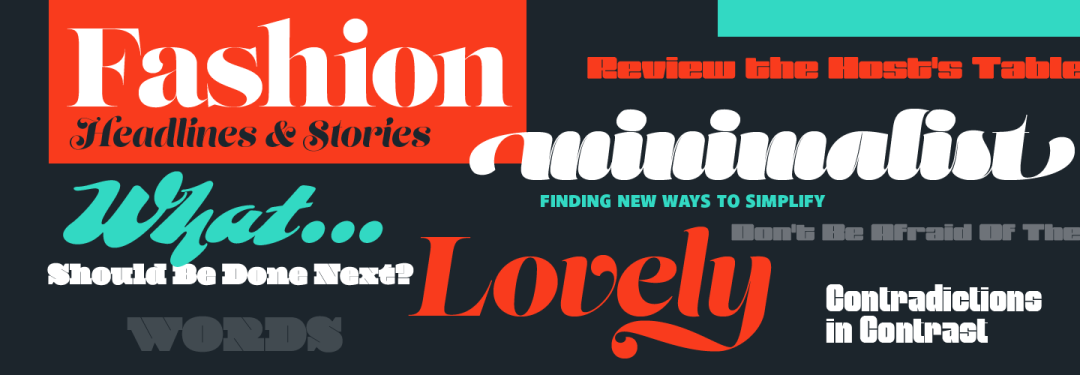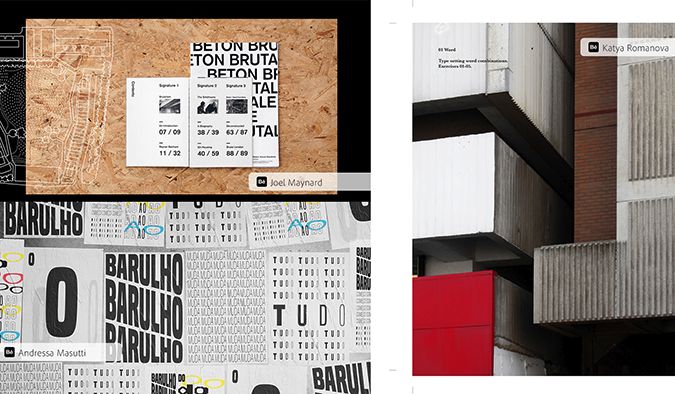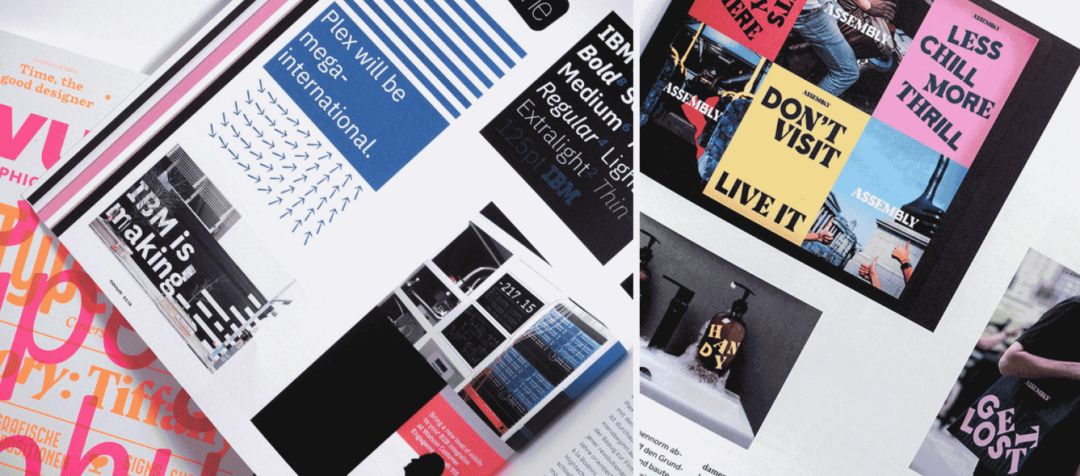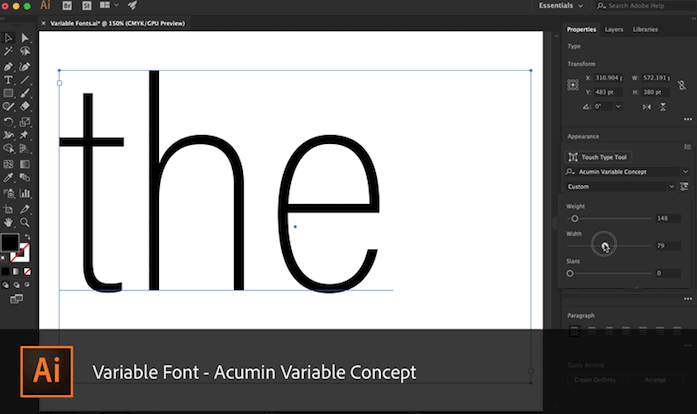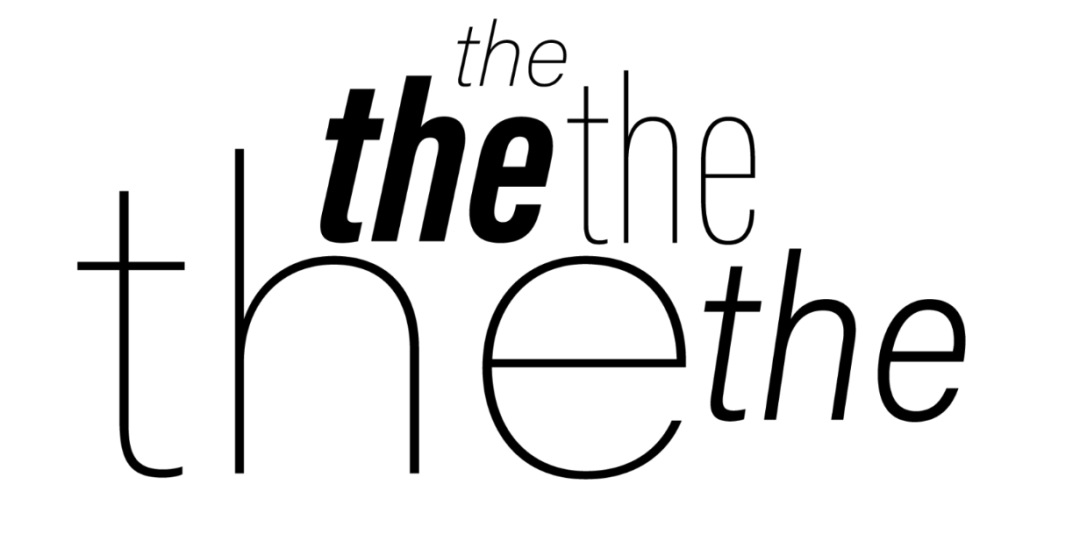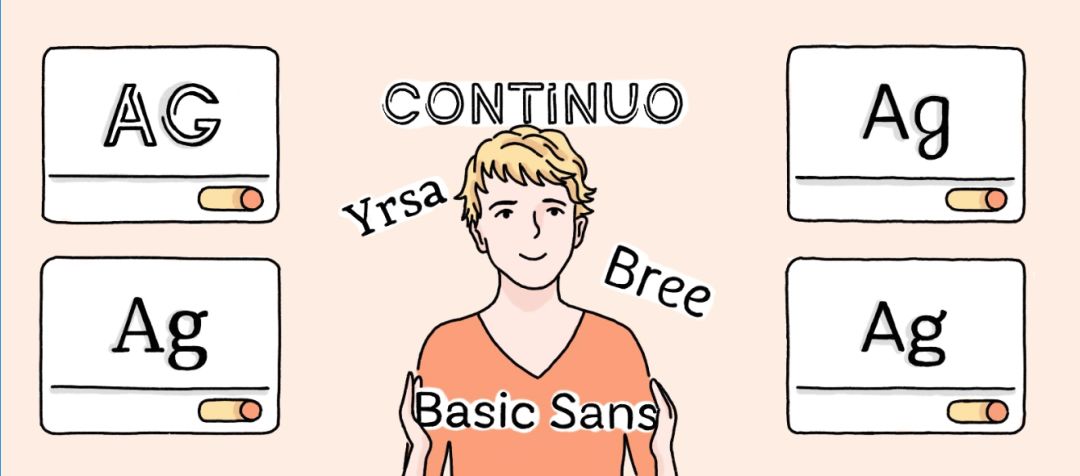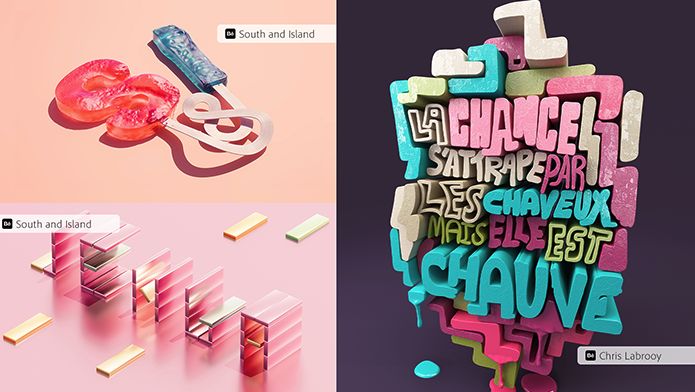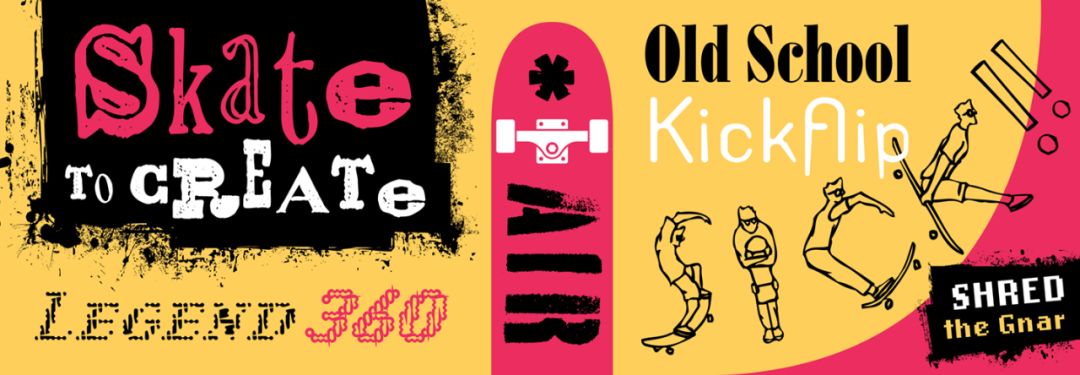
2019八大排版设计趋势,Adobe官方推荐!
Adobe收集了今年最激动人心的排版趋势。
“需要帮助人们了解如何看待排版比以往任何时候都更重要。”
作为设计师,我们现在比以往更依赖排版趋势来讲述设计中的故事情节,并且通过更多工具和创新字体。
让我们来看看2019年你应该知道的前8个排版趋势。
1.最小的Sans Serifs(衬线字体)
“Sans Serifs永远不会死。”
无衬线字体在平面设计方面做出了相当大的声明 。他们略微复杂的现代神秘感赋予设计师创造表达和情感的空间。我们还将无衬线字体视为“清洁”工作的新标准。“现代的San Serifs已成为像Helvetica这样的非企业主流声音的代言人,”Papaelias说。这里有一些你应该尝试的Sans Serif字体。
2.高对比度
Adobe Fonts这样的工具提供了一个可以拥有更多自由范围的地方,其中包括厚度和厚度,重叠和间距。以下是您应该探索的一些高对比度字体。
3.粗犷
“能做些什么,不应该这样做?”
野蛮主义就是直接推向前沿 - 许多设计师正在尝试尝试他们不应该做的事情的趋势。“这是一种新的后现代时代。对规则和标准有真正的反应。“野蛮主义是在你的设计中创造视觉张力的好方法。”
当一个设计呈现原始和未经抛光时,它会引起人们的注意。野兽派排版可以唤起一种急躁和反叛的语调,这就是为什么我们看到这种风格常用于海报和实验艺术。
4.可变字体+动力学类型
“可能是最伟大的发现之一。”
随着Open face类型的新创新,曾经缺乏想象力的简单字体和图形处理现在可以用于无限的自定义,可用于放大设计。
使用可变字体,您现在可以将类型增大,缩小,拉伸和弯曲到任何给定的范围,屏幕或平台,以创建比例平衡,一致性甚至动画。
Papaelias说:“这是一个技术可能以有趣的方式开始通知设计决策的地方。”如果你想要摆脱静态设计,可变字体很有用。您拥有更多的风格自由,以及在设计中使类型更具交互性的能力。
5.大胆自信 +概述
正如他们所说的那样,越大越好,并且通过排版,对你的声音大小没有限制。所有大写字母,小写字母和过度拥挤都是头脑。
概述类型也有趣地过渡到平面设计。经常在时尚和社论中看到,概述赋予字体在开放作品和其他对象中很好地演奏的能力。
颜色字体永远不会与设计疏远。玩今年的视觉趋势调色板每次都会吸引人们的注意力。
6.手写字体
“个性比以往任何时候都重要。”
我们知道,手刻字是无处不在。但是这种技术还有更多要说的,特别是当我们探索个人风格时。“手刻字是一种模仿笔迹的类型字体的门户药物已经存在了很长一段时间,在西方文化中,大多是女性审美。”
在过去几年中,我们注意到手工刻字变得更加透明,采用了一系列风格的表达方式,色调感觉不那么女性化或“校舍”类型,更加大胆,质朴和前卫。手刻字有很多细微差别; 它赋予了艺术家更多的独特性,无法轻易复制。
7.怀旧字体
我们都想要找到80年代的完美字体参考,是对的吗?
印刷工人Ed Benguiat创造了一种让人想起恐怖经典和80年代流行文化的风格。因此,不可避免地,怀旧总会在设计中出现。
将它们用于电影海报,现场音乐传单和活动公告等项目。这里有一些你应该玩的怀旧90字体。
8.AR的3D +类型
随着设计师开始尝试更多新的尺寸空间,我们如何考虑排版的作用?
借助围绕VR,AR和照片般逼真造型的全新设计创新,三维类型可以更加自由流动,与周围环境相互作用。
设计师,你准备好了吗?